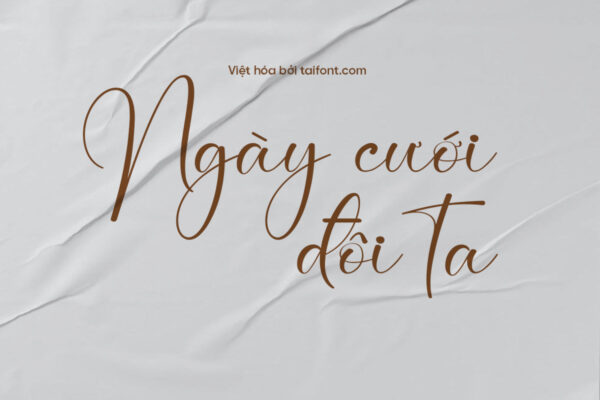
Giới thiệu về Font TF Handwritten Việt hóa
TF Handwritten Việt hóa là một font chữ viết tay (script font) nổi bật với thiết kế thanh mảnh, uyển chuyển và đầy tinh tế. Font này mang đến vẻ ngoài mềm mại, sang trọng và rất riêng, gợi cảm giác như một ghi chú viết tay một cách tự nhiên và đầy cảm xúc, lý tưởng để tạo điểm nhấn độc đáo và thu hút mọi ánh nhìn trong các thiết kế đòi hỏi sự cá tính và sự thanh lịch.
Với đặc điểm là nét viết tay mềm mại, phong cách tự nhiên và tính thẩm mỹ cao, Handwritten là lựa chọn hoàn hảo cho các ấn phẩm muốn truyền tải sự nhẹ nhàng và phong cách, đặc biệt là trong các lĩnh vực:
- Thiết kế thiệp cưới: Hoàn hảo để viết tên cô dâu chú rể, lời mời cưới, hoặc các thông tin chi tiết trên thiệp cưới, menu tiệc, bảng tên khách mời. Nét chữ mềm mại của font sẽ biến mỗi tấm thiệp thành một tác phẩm nghệ thuật, mang đậm dấu ấn cá nhân và sự lãng mạn, trang trọng.
- Thiết kế thiệp mời: Lý tưởng để sử dụng cho logo, tagline hoặc bộ nhận diện thương hiệu của các công ty, doanh nghiệp muốn truyền tải sự tinh tế, uy tín và sự thanh lịch. Font này giúp tạo dấu ấn cá nhân, sự phá cách và độc đáo cho thương hiệu.
- Thiết kế bao bì và sản phẩm: Phù hợp cho bao bì sản phẩm thủ công, đặc sản địa phương, hoặc các sản phẩm có phong cách vintage, mộc mạc. Font này giúp sản phẩm trở nên nổi bật và thu hút.
- Thiết kế nội dung và trích dẫn: Tuyệt vời để tạo các câu trích dẫn đầy cảm hứng, slogan hoặc các dòng chữ cần sự nổi bật và mang tính biểu cảm trên mạng xã hội hoặc các ấn phẩm khác, đặc biệt khi kết hợp với hình ảnh mang hơi hướng cổ điển hoặc nghệ thuật.
Với TF Handwritten Việt hóa, bạn có thể dễ dàng thổi hồn tinh tế, nhẹ nhàng và vẻ đẹp hoàn hảo vào các thiết kế, tạo ra những sản phẩm không chỉ đẹp mắt mà còn đầy cảm xúc và sức hút đặc biệt.
Font Việt hóa TF Handwritten